2024年に開催した企画展「活字の種を作った人々」が本になりました! 刊行記念イベントとして、8/8(土)に、著者の雪朱里さん(展示では企画協力)と展示企画担当のふたりで、書籍化のビハインドや、種字を彫った彫刻師エピソードをご紹介してまいります。
2024年に開催した企画展「活字の種を作った人々」が本になりました!
『活字の種をつくった人々』(水鈴社刊)刊行記念イベントとして、8/8(土)に、著者の雪朱里さん(展示では企画協力)と展示企画担当のふたりで、書籍化のビハインドと、あらためて種字彫刻師についてお話していきます。
マッチ棒より細い木や地金の先端に、原寸・逆向きに複雑な文字を彫ることのできる種字彫刻師は、印刷の歴史の中でなくてはならない存在でした。しかしながら、彫刻師の名前や、誰がどんな書体を彫ったかについて、あまり多くは資料が残っていません。本書では種字彫刻師について、数少ない資料をひもときながら、ひとりずつご紹介しています。
そして本書は、「ぜひこの種字彫刻師について、本に残したい」と雪さんが情熱を注いで、ついに一冊にまとまりました。
わたしたちの身近にある書体を生み出してきた種字彫刻師について、本書をきっかけに、あらためて多くの皆さんに知っていただきたいです。
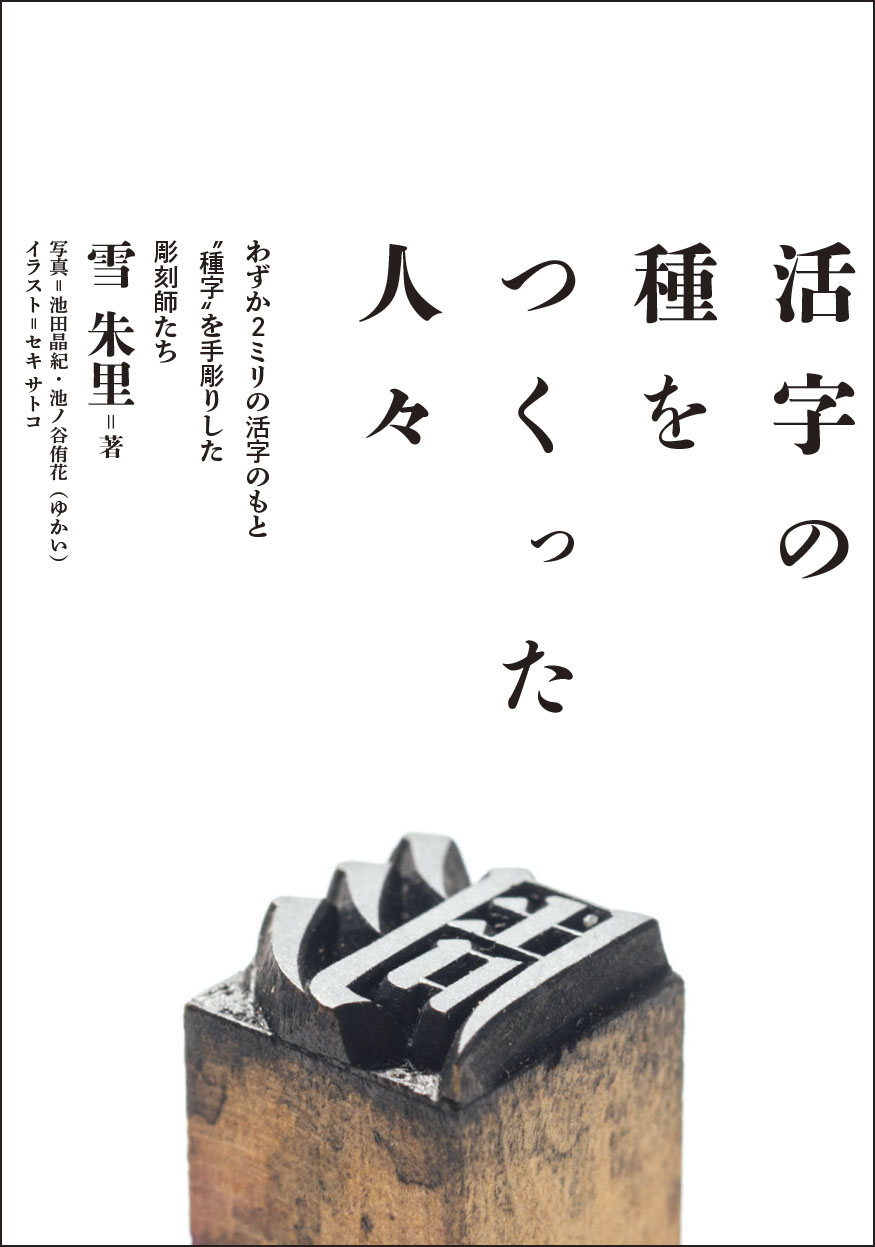
活字の種をつくった人々
わずか2ミリの活字のもと “種字” を手彫りした彫刻師たち
私たちの身のまわりにある本や雑誌、新聞。そこに並ぶひとつひとつの文字は、40年ぐらい前までは、おもに活版印刷で刷られていました。活版印刷とは、ハンコのような鉛の活字を組み合わせて、機械で印刷する方法です。ひとつひとつの文字は、1本1本の鉛活字を並べることで刷られていましたが、その鉛活字のおおもとの型を、かつて人が手で彫っていたことを知っていますか?――活字とおなじ大きさ、デザイン、鏡文字で。
文章のなかには、おなじ文字が何度も登場します。このため、たとえば1冊の本をつくるために、「あ」なら「あ」の鉛活字を何十本も用意しておかなくてはなりません。場合によっては何百本、何千本も。「母型(ぼけい)」というひとつの型から量産するのですが、そのためには必ずだれかがその「母型」のおおもととなる型=「種字(たねじ)」をつくる必要がありました。描いたり、写したりするのではありません。木や鉛合金でできたマッチ棒ぐらいの小さな細い軸に、人の手で「彫って」つくられたのです。
原寸大ですから、本文用でもわずか2、3ミリ角の大きさです。そのサイズに彫刻刀で、それも鏡文字で彫って、明朝体やゴシック体、楷書体など、いろいろなデザインの種字がつくられ、活字のもと=種になった。にわかには信じられないような話ですが、明治から昭和にかけて、実際におこなわれてきたことなのです。この種字を彫る職人のことを、「種字彫刻師」といいました。
はたして、「種字彫刻師」の仕事とは、どのようなものだったのでしょうか。そして「種字彫刻師」とは、どんな人たちだったのでしょうか。本書では、いま、私たちの身のまわりにあるスマートフォンやパソコン、本、雑誌、新聞などのなかに、当たり前のように表示され、印刷されている文字。そんな文字――フォントの源流といえる文字を彫っていた「種字彫刻師」の人と仕事を、わずかに残された資料や実物からひもときます。